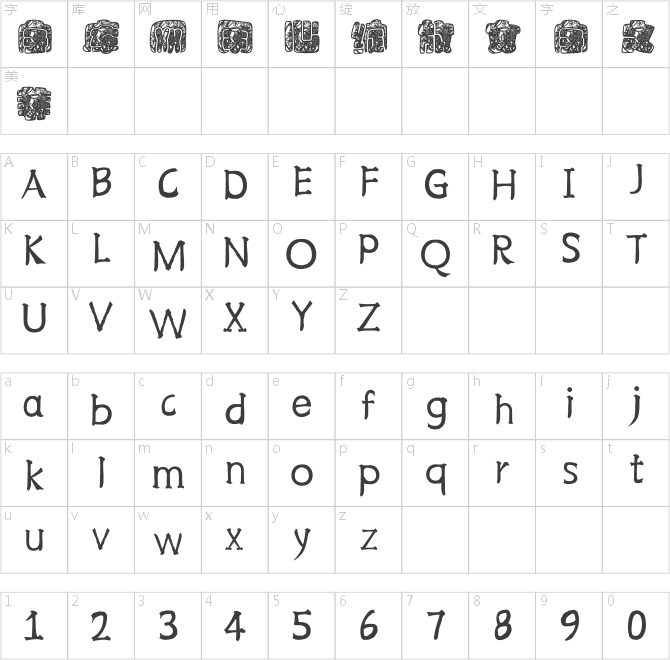
邯鄲說(shuō)媒兔剪紙
邯鄲說(shuō)媒兔剪紙?bào)w字體字庫(kù)是一款讓人賞心悅目、百看不厭的中文字體,適合各類廣告和產(chǎn)品包裝設(shè)計(jì)應(yīng)用,字體大小31.76MB,格式為ttf字體,上傳用戶是邯鄲字庫(kù),作者/版權(quán)方為邯鄲字庫(kù)